27 лучших шрифтов для визиток 2023 года (бесплатно и премиум)
Опубликовано: 2023-12-12Вы графический дизайнер и ищете идеальный шрифт, который улучшит дизайн ваших визитных карточек? Возможно, вы устали использовать одни и те же старые шрифты и хотите изучить новые варианты, которые действительно выделят ваши проекты.
Что ж, вы пришли в нужное место! В этом сообщении блога мы покажем 27 лучших шрифтов для визитных карточек, которые превратят ваш дизайн из обычного в необычный.
Теперь вам может быть интересно, почему шрифты так важны для дизайна визитных карточек. Правда в том, что шрифты играют решающую роль в передаче правильного сообщения и задании тона вашего бренда. Они могут вызвать разные эмоции и произвести неизгладимое впечатление на получателей ваших визиток.
Фактически, исследования показали, что выбранный вами шрифт может повлиять на то, как люди воспринимают ваш бренд, и даже повлиять на их решения о покупке.
В этой статье мы тщательно составили список из 27 лучших шрифтов для визитных карточек, которые не только визуально привлекательны, но и очень эффективны в привлечении внимания и оставлении неизгладимого впечатления.
Ищете ли вы классический и элегантный шрифт для профессиональной визитной карточки или смелый и уникальный шрифт для творческого проекта, мы предоставим вам все необходимое. Так что расслабьтесь, расслабьтесь и давайте окунемся в чудесный мир шрифтов для визиток!
Лучшие шрифты для визитных карточек премиум-класса
Хотите улучшить дизайн своей визитной карточки? Не смотрите дальше! Наша тщательно подобранная коллекция премиальных шрифтов для визитных карточек обязательно произведет впечатление и выделит вашу визитку среди остальных. Найдите идеальный шрифт для улучшения вашего проекта, просмотрев наш список ниже. Не упустите эти первоклассные варианты!
Розовый закат
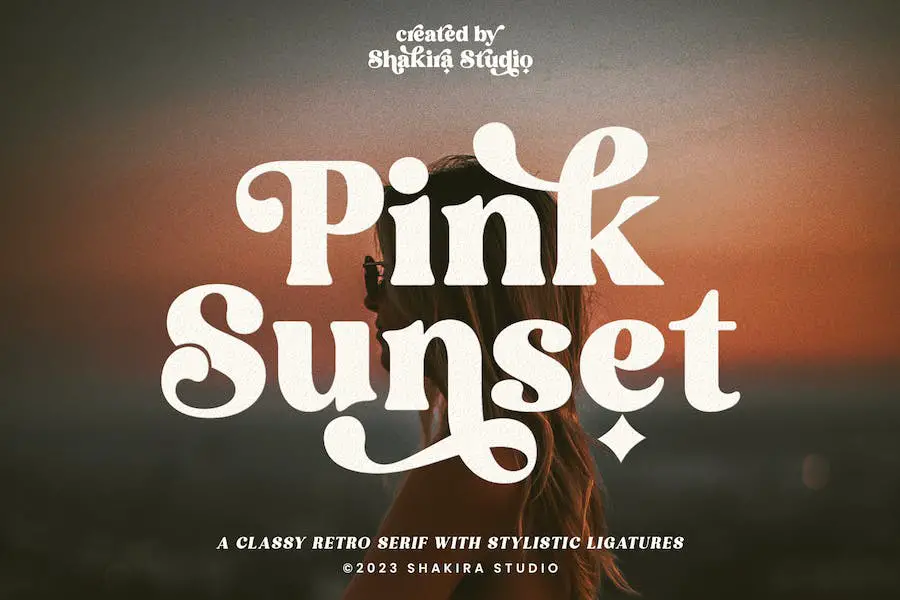
Pink Sunset — это современный шрифт для визитных карточек, который придаст вашим проектам уникальный винтажный вид. Благодаря более чем 50 уникальным вариантам альтернатив и лигатур этот шрифт идеально подходит для создания логотипов, визитных карточек и других выдающихся дизайнов.
Его стильный внешний вид в стиле ретро придает нотку элегантности смелым заголовкам и изысканному дизайну. Контрастные линии и изогнутые терминалы Pink Sunset придают изящный и красивый вид различным проектам, включая праздничные открытки, свадебные приглашения, цитаты и рекламу.
Не упустите возможность придать своей работе винтажный оттенок с помощью этого универсального шрифта.
Шрифт Халва
Halva Font — профессиональный округлый шрифт, который идеально подходит для различных деловых целей, включая дизайн визитных карточек, макетов журналов, рекламный дизайн, модные проекты, веб-дизайн, обложки книг и плакаты.
Закругленные края придают ему современный и элегантный внешний вид, что делает его отличным выбором для тех, кто хочет улучшить дизайн своих проектов.
Кроме того, чистые линии и сбалансированные пропорции шрифта способствуют его общей читабельности, гарантируя, что ваше сообщение будет передано четко и эффективно.
Еще одним преимуществом шрифта Halva является его универсальность в различных вариантах дизайна. Независимо от того, разрабатываете ли вы стильный и современный веб-сайт или создаете смелый и привлекательный постер, этот шрифт легко вписывается в различные стили дизайна.
Его простота позволяет адаптироваться к различным цветовым схемам и графическим элементам, не перегружая общий дизайн. Эта гибкость особенно ценна для графических дизайнеров, которые работают над широким спектром проектов с разнообразной эстетикой.
Пятница
Friday's Font — фантастический и элегантный шрифт, который идеально подходит для самых разных проектов. Благодаря тонкому и элегантному дизайну он идеально подходит для визитных карточек, обложек книг, презентаций и многого другого.
Если вы хотите добавить изысканности своим приглашениям или создать привлекательный дизайн блога, Friday's Font поможет вам. Этот универсальный шрифт также отлично подходит для любителей DIY, которые хотят создавать красивые поделки ручной работы или макеты для скрапбукинга.
Четкие линии и разборчивые символы делают его лучшим выбором для всех ваших потребностей в печатной бумаге. Не упустите возможность улучшить свои дизайнерские проекты с помощью Friday's Font.
Материнство
Maternity Font — изысканный и утонченный шрифт, который добавит элегантности любому дизайнерскому проекту. Работаете ли вы над свадебным приглашением, визитной карточкой, рекламой или даже упаковкой продукта, шрифт Maternity Font — идеальный выбор для шрифтов Google Business Card.
Его красота и класс делают его идеальным для логотипов, канцелярских товаров, цитат и многого другого. Благодаря своей вневременной привлекательности этот шрифт обязательно улучшит общий вид ваших проектов.
Минья
Minya – Modern Retro Serif – шрифт, воплощающий возрождение ретро-эстетики. В своей версии Outline этот шрифт предлагает более 34 различных альтернатив и лигатур, что позволяет придать вашему логотипу, визитной карточке и другим дизайнерским проектам уникальный винтажный оттенок.
Minya не только имеет традиционный вертикальный стиль, но также включает в себя курсивную версию, что дает вам еще большую универсальность в ваших проектах.
Этот шрифт с засечками легко сочетает в себе элементы современного и ретро-стилей, что делает его идеальным выбором для тех, кто хочет создать ностальгический, но при этом элегантный дизайн.
Его версия Outline добавляет дополнительный уровень глубины и характера, что делает его идеальным для логотипов, упаковки, редакционных макетов и различных других творческих начинаний. Кроме того, Minya может похвастаться высоким уровнем разборчивости, гарантируя, что ваше сообщение будет четко донесено до зрителей.
Мунале Лойрд
Munale Loird Display Font — это новый стильный шрифт с засечками, выполненный в минималистском и шикарном стиле. Он был создан с любовью и вниманием к деталям, что делает его не только удобным, но и очень стильным, а визитная карточка также подходит для шрифтов Adobe.
Этот шрифт идеально подходит для различных дизайнерских проектов, включая дизайн брендинга, логотипов, свадебных приглашений, заголовков, плакатов и визитных карточек. Благодаря своему гладкому и элегантному дизайну шрифт Munale Loird Display Font обязательно поднимет ваши проекты и придаст им профессиональный и изысканный вид.
Так что, если вы графический дизайнер и ищете шрифт для улучшения своих проектов, обязательно обратите внимание на Munale Loird Display Font.
Амброзиал
Представляем Ambrosial Font — очаровательный и элегантный рукописный шрифт, излучающий класс и женственность. Этот универсальный шрифт — идеальный выбор для широкого спектра дизайнерских проектов, включая приглашения, визитные карточки, логотипы и брендинг.
Благодаря своему романтическому стилю Ambrosial Script придает любому дизайну нотку изысканности и очарования. Так что смело берите этот шрифт в свою коллекцию – мы надеемся, что вам понравится красота и элегантность Ambrosial Script!
Вельгифе
Velguife Font — это простой и стильный рукописный шрифт, который придаст элегантность и стиль вашим дизайнерским проектам. Благодаря своей читабельности и стильной привлекательности этот шрифт обязательно привлечет внимание вашей аудитории.
Одним из ключевых качеств шрифта Velguife является его читабельность и качество текста. Гладкие и разборчивые символы гарантируют, что ваш текст будет легко понятен даже при небольшом размере.
Это особенно важно при разработке визитных карточек или других материалов, где пространство ограничено. Используя шрифт Velguife, вы можете быть уверены, что ваше сообщение будет передано четко и эффективно.
Еще одна выдающаяся особенность шрифта Velguife — его запоминаемость. Уникальный и привлекательный дизайн шрифта привлекает внимание и оставляет неизгладимое впечатление на вашу аудиторию.
Независимо от того, используете ли вы его для публикаций в социальных сетях, рекламы или дизайна продуктов, шрифт Velguife выделит ваш контент и привлечет интерес зрителей.
Тропический поток
Шрифт Tropical Flow — невероятно забавный и универсальный шрифт, который идеально подходит для всех ваших повседневных дизайнерских проектов. Будь то для печати или для Интернета, этот шрифт обязательно добавит игривости вашим творениям.
Шрифт Tropical Flow идеально подходит для логотипов, приглашений, визитных карточек и многого другого. Он предлагает безграничные возможности для ваших профессиональных дизайнерских потребностей. Он особенно удобен для добавления уникальной подписи или водяного знака к вашей фотографии, создания потрясающих обложек альбомов или демонстрации индивидуальности вашего бренда.
Благодаря широкому спектру применений этот шрифт является обязательным для графических дизайнеров, стремящихся улучшить свои проекты. От цитат до публикаций в социальных сетях, рекламы и дизайна продуктов — шрифт Tropical Flow привнесет яркую тропическую атмосферу в любой дизайнерский проект. Придайте своей работе свежий и увлекательный вид с помощью шрифта Tropical Flow.
Зимняя Леди
Winterlady Font — красивый рукописный шрифт, который привнесет элегантность и очарование в любой дизайнерский проект. Работаете ли вы над упаковкой продукта, брендингом, созданием визитных карточек или дизайном для социальных сетей, этот шрифт обязательно улучшит вашу работу. Это также отличный выбор для свадебных приглашений или любого проекта, где вы хотите выразить слова стильно и изысканно.
С помощью шрифта Winterlady вы сможете добавить в свой дизайн нотку женственности и изящества. Плавные линии и сложные детали делают его универсальным выбором для различных целей. Хотите ли вы создать романтический образ или изысканную атмосферу, этот шрифт поможет вам.
Одна из замечательных особенностей Winterlady Font — это его гибкость. Вы можете легко сочетать его с другими шрифтами, чтобы создать уникальный и целостный дизайн. Хотите ли вы объединить его с жирным шрифтом без засечек для придания современного вида или соединить его с классическим шрифтом с засечками для создания вневременного ощущения, возможности безграничны.
Шрифт Winterlady — универсальный выбор для любого проекта. Он хорошо работает как с маленькими, так и с большими размерами, гарантируя, что ваш текст останется четким и разборчивым независимо от масштаба. Итак, независимо от того, создаете ли вы небольшую визитную карточку или большую вывеску, этот шрифт даст потрясающие результаты.
Помимо эстетической привлекательности, шрифт Winterlady еще и очень прост в работе. Его плавные изгибы и правильно сформированные буквы позволяют легко читать и использовать его в любом дизайнерском проекте. С помощью этого шрифта вы без труда сможете создавать красивые и профессионально выглядящие проекты.
Халоха
Шрифт Haloha — это потрясающий рукописный шрифт, который добавляет элегантности и гармонии любому дизайнерскому проекту. Этот шрифт, вдохновленный летней темой, излучает непринужденность и естественность.
Независимо от того, создаете ли вы логотип, этикетку, название, заголовок, продукт, публикацию в социальных сетях, визитную карточку или цитату, Haloha — идеальный выбор для повышения индивидуальности вашего бренда. Благодаря универсальному и эстетичному дизайну этот шрифт гарантированно выделит ваши проекты.
Гамильтон
Hamilton Font — универсальный и стильный шрифт, который идеально подходит для различных дизайнерских проектов. Он специально разработан для модного дизайна, подписей, логотипов, брендинга, водяных знаков, фотографий и визитных карточек. Благодаря форматам TTF, OTF и WOFF к нему можно легко получить доступ и использовать его без необходимости использования дополнительного программного обеспечения для проектирования.
Шрифт также содержит символы в кодировке PUA, и эти шрифты для визитных карточек полезны для Canva.
, что позволяет пользователям получать доступ к альтернативным глифам для дополнительной настройки.
Реляшн Де Люкс
Шрифт Relation De Luxe — это современный и классический парный шрифт, который придаст очарование любому дизайнерскому проекту. Благодаря своим округлым и размытым эффектам этот шрифт идеально подходит для создания логотипов, брендинговых материалов, обложек журналов, публикаций в социальных сетях, цитат, свадебных приглашений, упаковочных этикеток и визитных карточек.
Его универсальность делает его незаменимым для графических дизайнеров, желающих улучшить свои проекты с помощью стильного и уникального шрифта. Независимо от того, работаете ли вы над профессиональным или личным проектом, шрифт Relation De Luxe станет отличным выбором, чтобы добавить нотку элегантности и изысканности.
Ночь страха
Шрифт Fright Night — идеальный выбор для графических дизайнеров, которые хотят добавить нотку напряжения и привлечь внимание читателя. Этот эмоциональный шрифт с засечками излучает жуткую атмосферу, что делает его идеальным для любого проекта, в котором нужен намек на ужас.
Благодаря чистому и четкому дизайну Fright Night выделяется из толпы и добавляет уникальный элемент в ваши проекты.
Независимо от того, работаете ли вы над плакатами, названиями фильмов, рекламными щитами, брендингом или визитными карточками, этот шрифт универсален и может поднять ваш проект на новый уровень. Попрощайтесь со скукой и здравствуйте леденящей душу элегантностью шрифта Fright Night.
Мартинес
Martines Font — минималистичный, современный и стильный шрифт, который идеально подходит для любого проекта графического дизайна. Если вам нужен шрифт для заголовков или контента, Martines универсален и может улучшить ваш дизайн своим чистым и стильным внешним видом.
Этот шрифт идеально подходит для редакционных проектов, визитных карточек, книг, новостных статей, баннеров, листовок, логотипов, канцелярских товаров и многого другого. Его универсальность делает его подходящим как для небольших, так и для крупных работ. Шрифт для визитных карточек также хорош для татуировок.
Ксавиера
Шрифт Xaviera — это современный шрифт без засечек, разработанный специально для афиш фильмов, заголовков, печатных букв, подзаголовков, логотипов и больших баннеров. Это идеальный выбор для добавления творческих и декоративных нот в ваш типографский веб-дизайн.
Благодаря своему чистому внешнему виду и небольшому весу шрифт Xaviera идеально подходит для привлекательных заголовков. Он может прекрасно дополнять более декоративные и сложные шрифты подзаголовков, создавая визуально привлекательный и гармоничный дизайн.
Независимо от того, работаете ли вы над профессиональным проектом или над личным дизайном, Xaviera Font обязательно улучшит вашу общую эстетику. Его универсальность и пригодность для различных элементов дизайна делают его ценным инструментом для графических дизайнеров, стремящихся улучшить свои проекты.
Изящный и современный внешний вид шрифта Xaviera Font придаст любому дизайну нотку изысканности. Чистые линии и четко выраженные символы делают его очень разборчивым, гарантируя, что ваше сообщение будет легко понято зрителями.
Одной из выдающихся особенностей шрифта Xaviera Font является его способность привлекать внимание и сохранять читаемость даже при больших размерах. Это делает его отличным выбором для заголовков и заголовков, которые должны оказывать сильное воздействие.
Ортисан Подпись
Шрифт Ortisan Signature Font — идеальный выбор для добавления водяного знака на вашу фотографию, создания подписи или фирменного логотипа, включения вдохновляющих цитат, оформления обложки альбома, создания привлекательных визитных карточек и многого другого.
С Ortisan Signature ваша работа достигнет новых высот элегантности, класса, читабельности, стиля и привлекательности. Этот рукописный шрифт предлагает естественный и стильный стиль, который обязательно повысит эффективность ваших усилий по личному брендингу. Его рукописное качество придает индивидуальность любому проекту.
Регасто
Regasto Font — это шрифт с засечками, который излучает роскошь, элегантность, современность, уникальность и класс. Это идеальный выбор для графических дизайнеров, которые хотят придать своим проектам нотку изысканности. Благодаря прописным и строчным буквам, знакам препинания, цифрам, лигатурам и альтернативным символам Regasto предлагает широкий спектр возможностей, которые помогут вашему тексту течь естественно и придадут ощущение индивидуальности.
Regasto специально создан для проектов на тему роскоши, что делает его идеальным выбором для журналов, публикаций в социальных сетях, брендинговых материалов, логотипов и многого другого. Он добавляет тот дополнительный оттенок роскоши, который может превратить обычный проект в нечто экстраординарное.
Если вы хотите придать своим проектам современную и стильную атмосферу, Regasto Font — это то, что вам нужно. Его элегантная, изысканная и в то же время сильная эстетика обязательно произведет неизгладимое впечатление. Так зачем ждать? Поднимите свои проекты на новый уровень с помощью шрифта Regasto и позвольте своему творчеству проявиться.
Бандар
Bandar — универсальный шрифт, который можно использовать в различных дизайнерских проектах. Работаете ли вы над логотипом, дизайном брошюры, визитной карточкой или публикацией в социальных сетях, Бандар улучшит ваш дизайн. Благодаря чистому и современному стилю без засечек этот шрифт идеально подходит для создания профессионального и изысканного вида.
Семейство шрифтов Bandar включает пять различных начертаний: обычный, курсив, жирный, жирный курсив и контурный. Это дает вам возможность экспериментировать с разными стилями и создавать визуально привлекательный дизайн. Хотите ли вы сделать смелое заявление или добавить нотку элегантности, Бандар поможет вам.
Бандар подходит не только для демонстрации, но также хорошо работает и в меньших размерах. Это означает, что вы можете использовать его для различных элементов дизайна, таких как подписи, этикетки или упаковка продукта. Он добавляет изысканности вашим проектам, сохраняя при этом читабельность.
Универсальность Bandar делает его идеальным выбором для графических дизайнеров. Его чистые линии и современный стиль позволяют ему легко сочетаться с различными эстетиками дизайна. Создаете ли вы минималистичный фирменный стиль или яркий и игривый дизайн, Bandar дополнит ваше видение.
Лучшие бесплатные шрифты для визиток
Хотите улучшить дизайн своей визитной карточки? Не смотрите дальше! В этом разделе мы составили список лучших бесплатных шрифтов для визитных карточек, которые обязательно произведут неизгладимое впечатление. Не пропустите эти жемчужины типографики — обязательно ознакомьтесь с ними и улучшите свою игру с визитными карточками!
Веганский стиль
Шрифт Vegan Style — частичный и бесплатный шрифт исключительно для личного использования. Он предлагает графическим дизайнерам идеальный инструмент для улучшения дизайна своих проектов. Благодаря своим уникальным свойствам этот шрифт может по-настоящему улучшить ваши творения.
Одной из выдающихся особенностей шрифта Vegan Style является его современный и стильный дизайн. Он придает изысканность любой визитной карточке или дизайнерскому проекту, мгновенно привлекая внимание. Чистые линии и элегантный внешний вид делают его фантастическим выбором для тех, кто хочет сделать смелое заявление.
Помимо своей визуальной привлекательности, шрифт Vegan Style невероятно универсален. Широкий спектр символов и символов открывает безграничные возможности в ваших проектах. Независимо от того, создаете ли вы профессиональную визитную карточку или модный логотип, этот шрифт поможет вам.
Еще одним замечательным аспектом шрифта Vegan Style является его простота использования. Благодаря удобному интерфейсу даже новички смогут легко перемещаться и использовать этот шрифт. Его совместимость с различным программным обеспечением для проектирования обеспечивает плавную интеграцию в ваш рабочий процесс.
Красивые люди
Шрифт Beautiful People — это потрясающий и простой шрифт, который может значительно улучшить дизайн ваших проектов. Этот шрифт визуально привлекателен и легко читается, что делает его идеальным для визитных карточек и других нужд графического дизайна. Благодаря чистым линиям и элегантному внешнему виду Beautiful People придаст любому дизайну нотку изысканности.
Атрибуты Beautiful People — это то, что выделяет его среди других шрифтов. Его красота заключается в простоте, чистом и минималистичном дизайне, излучающем элегантность. Плавные изгибы и гладкие края этого шрифта придают ему изысканный и профессиональный вид, что делает его подходящим для широкого спектра дизайнерских проектов.
Одним из ключевых преимуществ использования шрифта Beautiful People является его универсальность. Его можно легко включить в различные конструкции, не нарушая общую эстетику. Независимо от того, создаете ли вы современную и элегантную визитную карточку или стильное и элегантное приглашение, этот шрифт органично впишется и повысит общую визуальную привлекательность вашего проекта.
Лимонное желе
Lemon Jelly — это шрифт, который добавляет нотку красоты и простоты любому проекту. Это красивый и простой вариант шрифта, который может улучшить дизайн визитных карточек и других проектов графического дизайна. Благодаря чистому и элегантному виду, это идеальный выбор для тех, кто хочет улучшить свой дизайн.
Одним из выдающихся качеств Lemon Jelly является его внешняя привлекательность. Изящные изгибы и чистые линии шрифта придают ему изысканный и изысканный вид, который мгновенно привлекает внимание зрителей. Он излучает ощущение элегантности и изысканности, что делает его подходящим для широкого спектра дизайнерских стилей и целей.
Помимо своей внешней привлекательности, Lemon Jelly еще и невероятно универсален. Его можно легко сочетать с другими шрифтами для создания уникального и целостного дизайна. Независимо от того, хотите ли вы создать современный и минималистичный образ или создать более игривую и причудливую атмосферу, Lemon Jelly может адаптироваться к вашим потребностям.
Еще одна замечательная особенность Lemon Jelly — его простота. Простой и лаконичный дизайн шрифта облегчает чтение и понимание. Он не перегружает и не отвлекает зрителя, позволяя сиять другим элементам вашего дизайна. Эта простота также хорошо подходит для создания чистой и профессиональной эстетики.
Марша
Marcha — идеальный и красивый шрифт, который идеально подходит графическим дизайнерам, которые хотят улучшить дизайн своих проектов. Благодаря своему элегантному и стильному внешнему виду Marcha придает элегантность любому дизайну визитной карточки.
Этот шрифт может похвастаться несколькими атрибутами, которые делают его лучшим выбором для графических дизайнеров. Во-первых, его чистый и современный вид гарантирует, что текст выделяется и его легко читать. Будь то название компании или контактная информация, Marcha не разочарует.
Кроме того, Marcha предлагает широкий выбор весов и стилей, что позволяет дизайнерам экспериментировать с различными вариациями, чтобы создать уникальный и привлекательный дизайн. Предпочитаете ли вы смелый и привлекающий внимание образ или утонченный и сдержанный вид, Marcha поможет вам.
ежевичный джем
Blackberry Jam — это частичный и бесплатный шрифт, который идеально подходит для личного использования. Он предлагает уникальный и стильный дизайн, который может улучшить проекты любого графического дизайнера. Благодаря своему элегантному и современному дизайну Blackberry Jam — отличный выбор для придания изысканности визитным карточкам и другим предметам дизайна.
Его простота и универсальность делают его ценным активом для любого графического дизайнера, желающего улучшить общий дизайн своего проекта.
Прославлять
Glorify — это демо-шрифт, предназначенный исключительно для личного использования, но создатели поощряют и ценят любые пожертвования. Важно отметить его ограничения с точки зрения использования. Однако даже в качестве демонстрационного шрифта Glorify предлагает ряд атрибутов, которые могут улучшить ваши дизайнерские проекты.
Одной из выдающихся особенностей Glorify является уникальный и привлекательный дизайн. Шрифт излучает индивидуальность и креативность, что делает его идеальным для привлечения внимания в дизайне визитных карточек. Его особый стиль добавляет элемент оригинальности вашим проектам, помогая вам выделиться из толпы.
Еще одним преимуществом Glorify является его универсальность. Шрифт хорошо работает как в больших, так и в маленьких размерах, что позволяет вам экспериментировать с различными макетами и дизайнами. Предпочитаете ли вы смелые и эффектные высказывания или элегантные и сдержанные шрифты, Glorify может адаптироваться к вашим потребностям и предпочтениям.
Белароза
Belarose — замечательный демонстрационный шрифт, предназначенный для личного использования. Его уникальные характеристики и стильный дизайн делают его любимым выбором графических дизайнеров для повышения визуальной привлекательности их проектов. Шрифт излучает элегантность и добавляет изысканности любому дизайну визитной карточки.
Belarose идеально подходит для тех, кто хочет оставить неизгладимое впечатление своим профессиональным брендом. Так что попробуйте этот шрифт, но имейте в виду, что он предназначен только для личного использования, хотя любое пожертвование в поддержку дизайнера приветствуется.
Сердце всего
The Heart of Everything — это шрифт, который улучшит дизайн ваших визитных карточек. Благодаря элегантному каллиграфическому стилю он придает изысканность любому проекту. Он идеально подходит для графических дизайнеров, которые хотят улучшить свои проекты и произвести неизгладимое впечатление.
Этот шрифт имеет вневременную привлекательность, что делает его универсальным для любой отрасли или типа бизнеса. Создаете ли вы визитные карточки для юридической фирмы, модного бренда или фотостудии, The Heart of Everything придаст вашим проектам ощущение профессионализма и элегантности.
С The Heart of Everything ваши визитные карточки будут выделяться среди остальных. Его уникальный и привлекательный стиль обязательно привлечет внимание потенциальных клиентов и оставит неизгладимое впечатление. Независимо от того, предпочитаете ли вы минималистичный дизайн или более сложный, этот шрифт обладает универсальностью и может адаптироваться к вашему творческому видению.
Часто задаваемые вопросы
При выборе шрифта для визитной карточки следует учитывать несколько факторов. Во-первых, читабельность является ключевым моментом. Вам нужен четкий и легко читаемый шрифт даже небольшого размера.
Во-вторых, учитывайте тон и индивидуальность вашего бренда. Выбранный вами шрифт должен соответствовать имиджу и ценностям вашего бренда. Наконец, подумайте об универсальности. Выберите шрифт, который достаточно универсален, чтобы его можно было использовать в разных дизайнах и материалах.
Хотя декоративные и рукописные шрифты могут добавить уникальности вашей визитной карточке, важно использовать их экономно и разумно. Эти шрифты лучше всего подходят для отраслей или брендов с более творческой или художественной направленностью. Если вы все же решите использовать декоративный или рукописный шрифт, убедитесь, что он по-прежнему разборчив и не ухудшает читаемость.
Да, некоторые шрифты хорошо подходят для профессиональных визитных карточек. Некоторые из лучших вариантов включают Helvetica, Garamond, Futura и Arial. Эти шрифты чистые, вневременные и широко признаны в деловом мире. Они передают профессионализм и традиции, что делает их пригодными для широкого спектра отраслей.
Заключение
В заключение мы рассмотрели 27 лучших шрифтов для визитных карточек, которые могут поднять ваши дизайнерские проекты на новый уровень. От элегантного и утонченного до современного и смелого — в этом списке есть шрифт для любого стиля и брендинга. Не забывайте экспериментировать и экспериментировать с различными комбинациями, чтобы найти идеальное сочетание шрифтов для вашей визитной карточки.